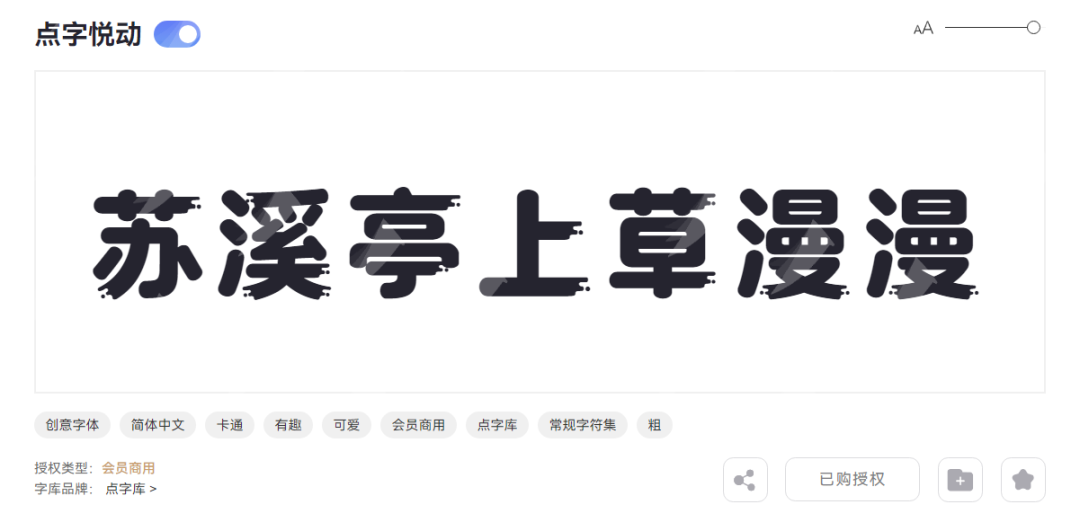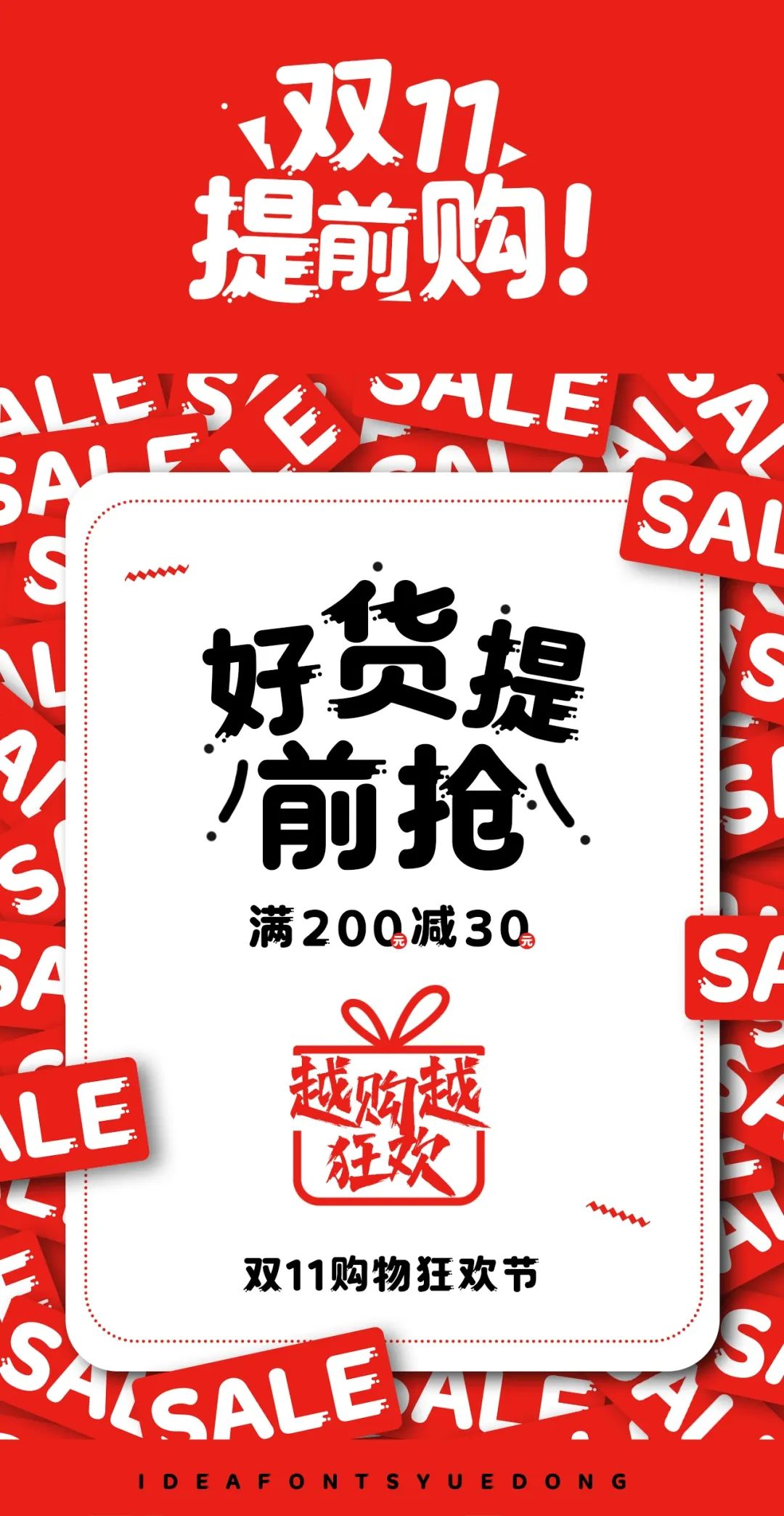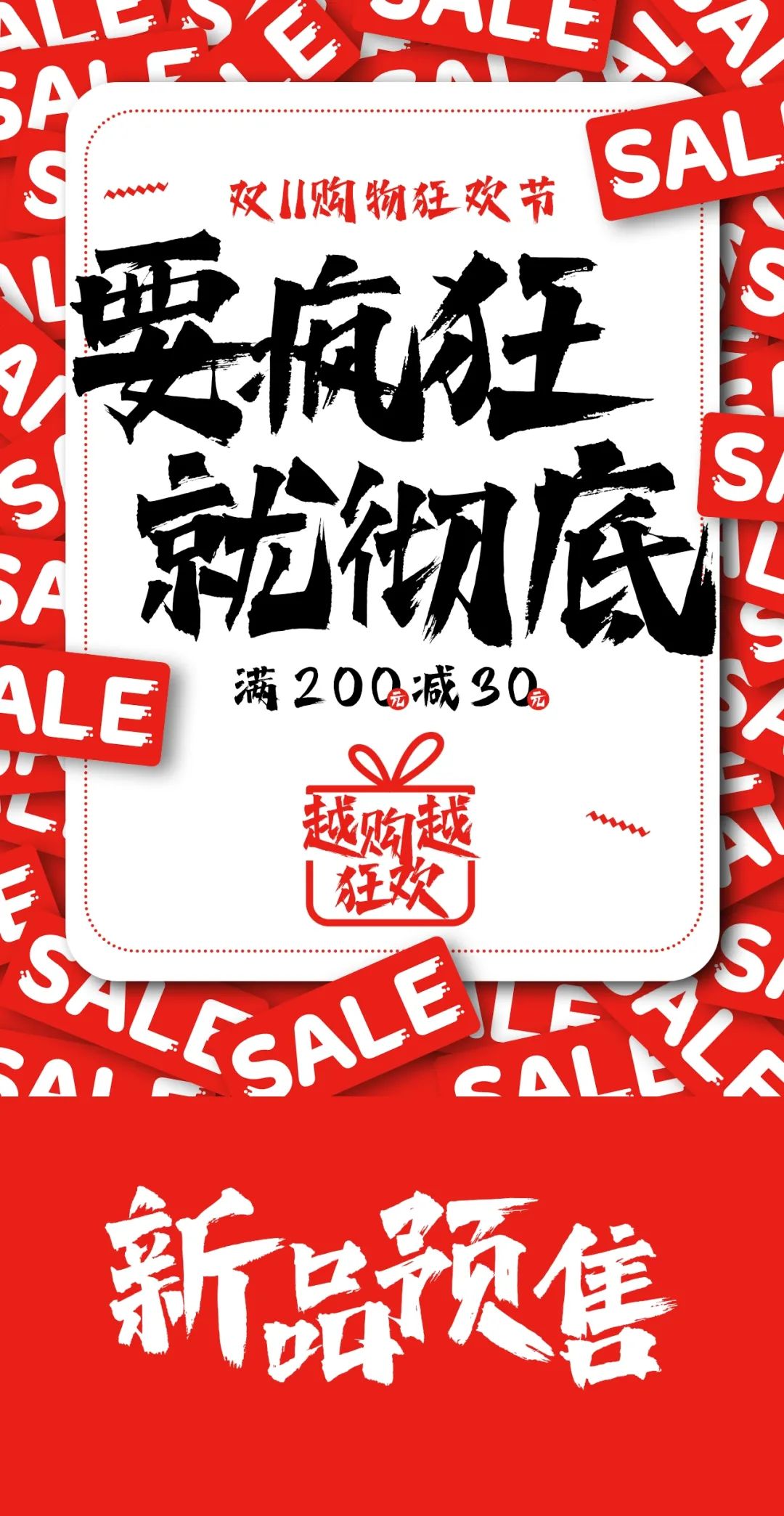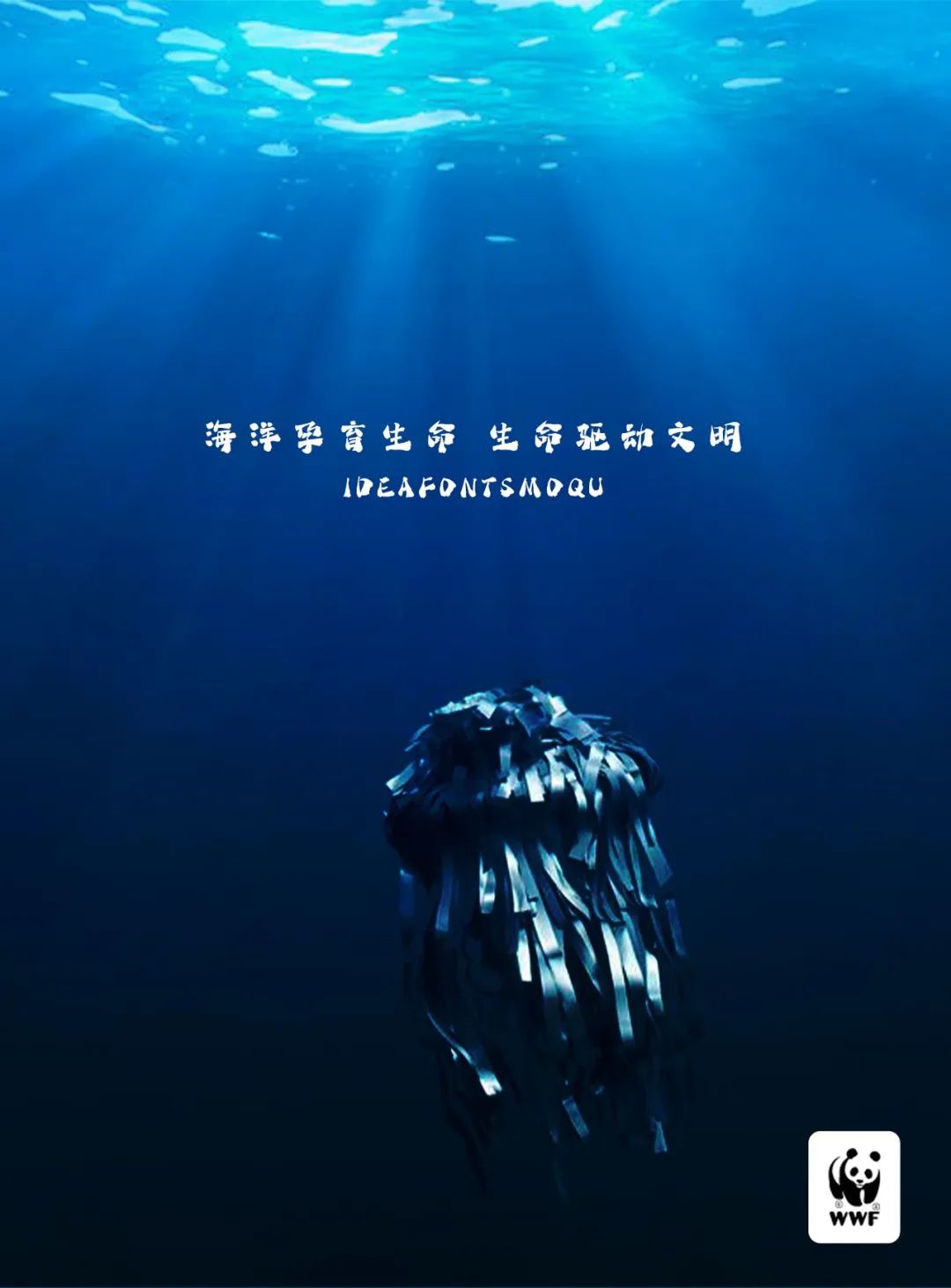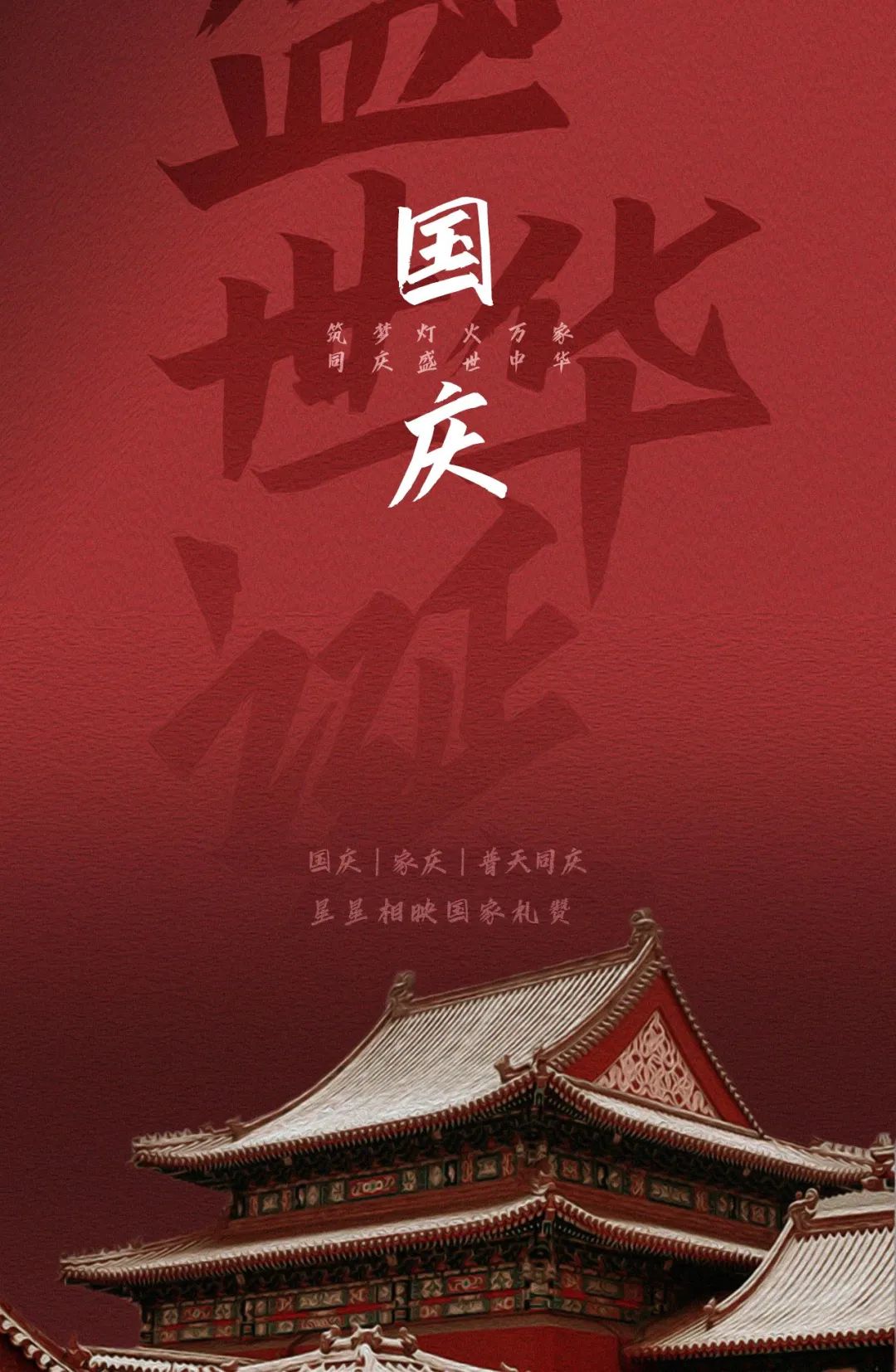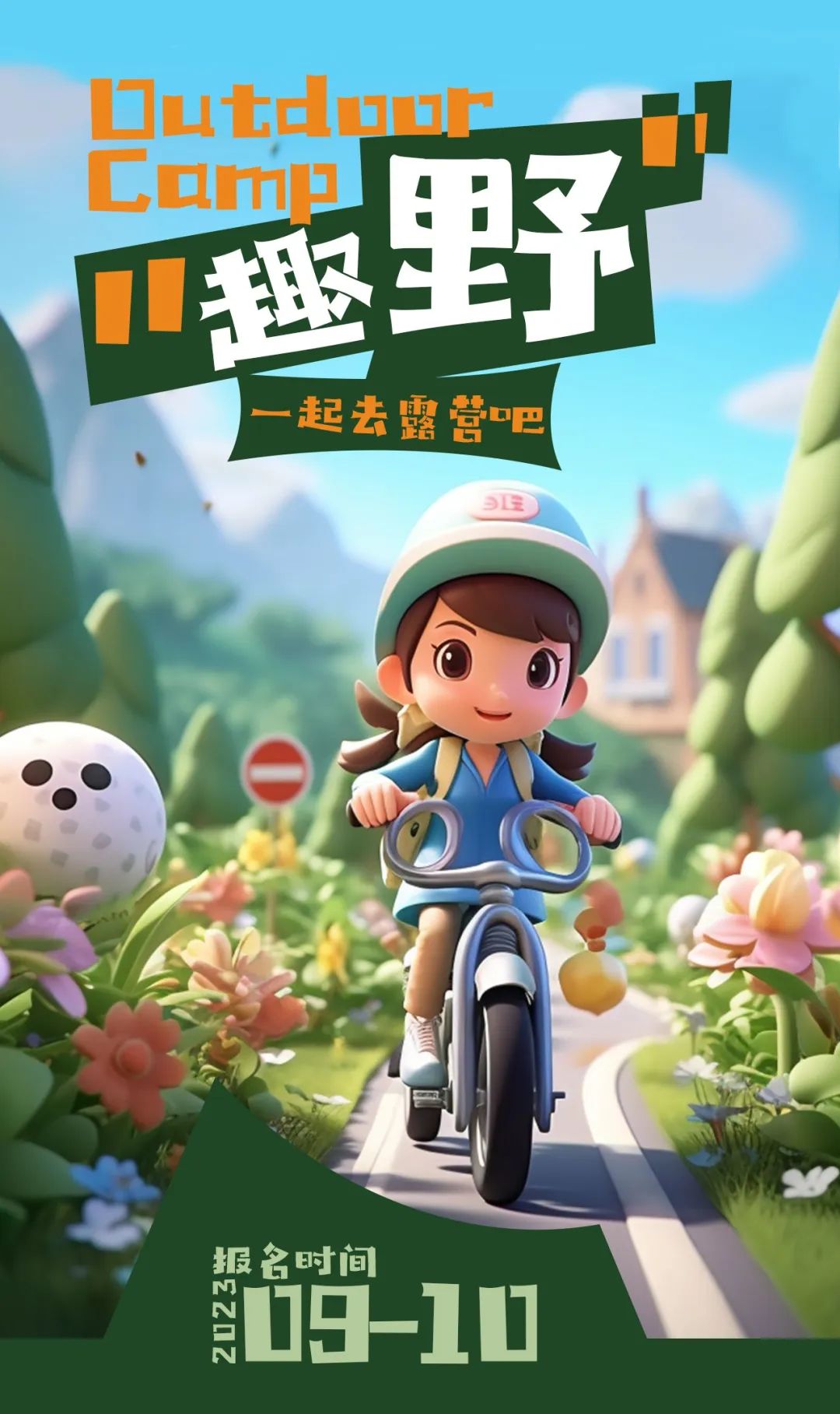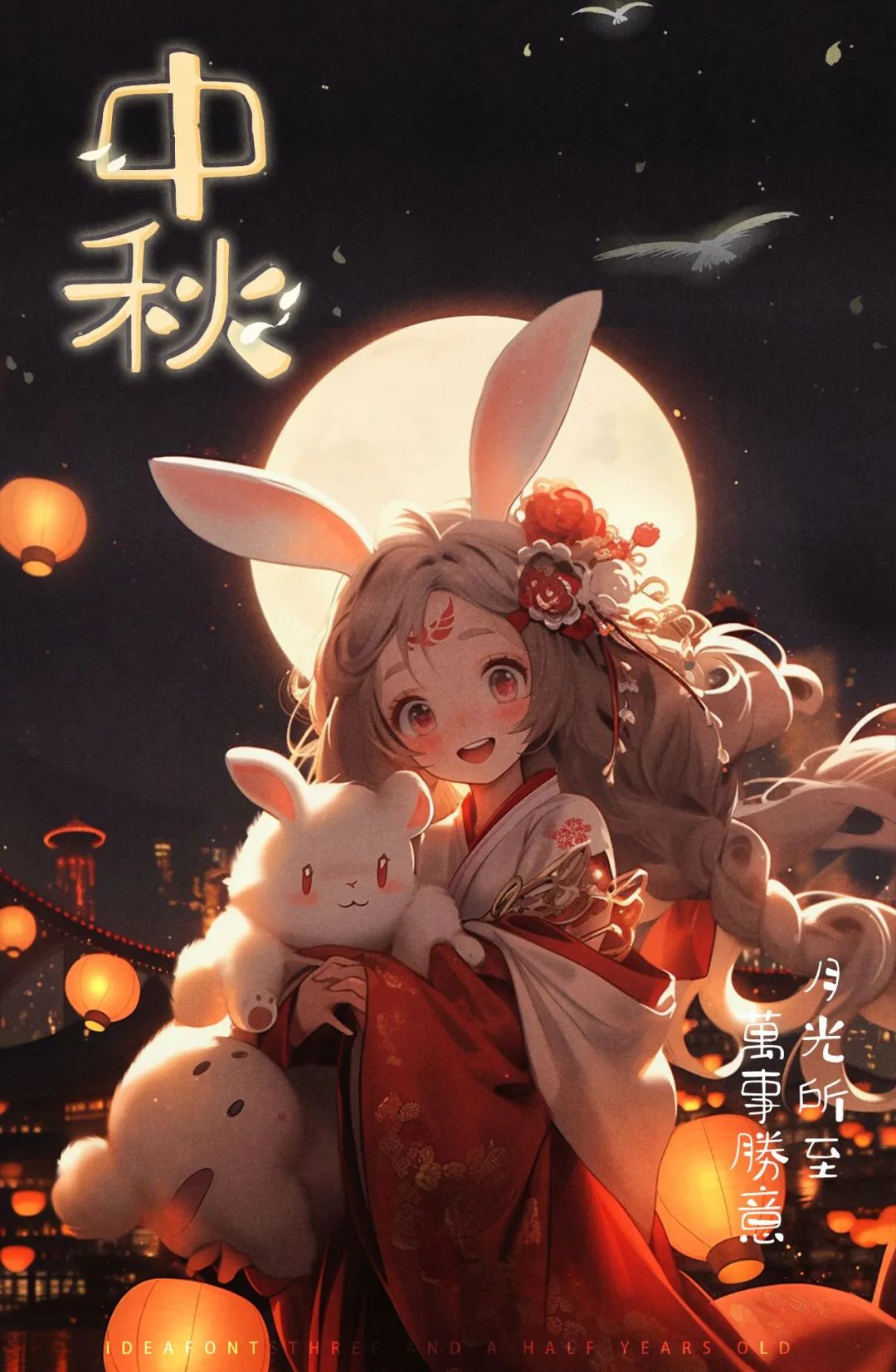
先来两张应景的,一个是点字将军令,看这笔触就够“疯狂”!
另一个是点字悦动,圆体的外观上,加入了末端的小细节,增加了韵律感,就像从漫画里走出来一样~
顺着这个思路,接下来就是手写字体+创意字体的show time
手写字体
首先是比较霸气比较粗的两款,点字乘风体和点字墨趣体,乘风体看笔画就很有气势,而墨趣体更有自然的拙朴感。
然后是比较百搭的两款字体,比如点字热烈体,点字潇洒体,代表了不同的个性,一个有点温柔,一个有点飒,放在哪里,都是挪不开眼的存在。
当然能提供多巴胺的可爱字体,也是必不可少,这次也带来了有点呆萌的点字涂鸦体,还有回味童年的点字三岁半。
最新的点字灵动体,粗中带细,与之相对的是点字拙书,憨得可爱。